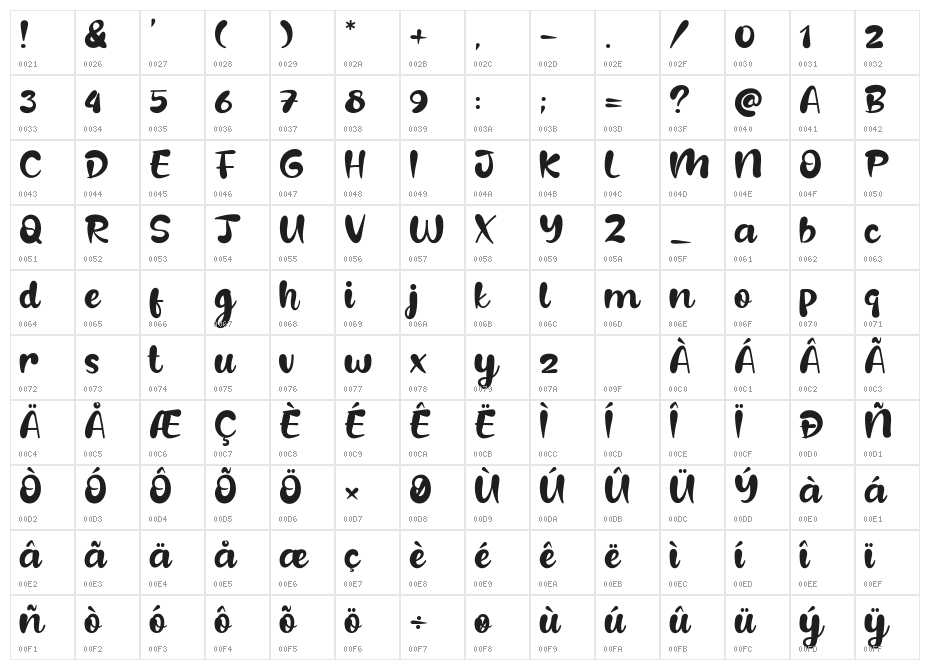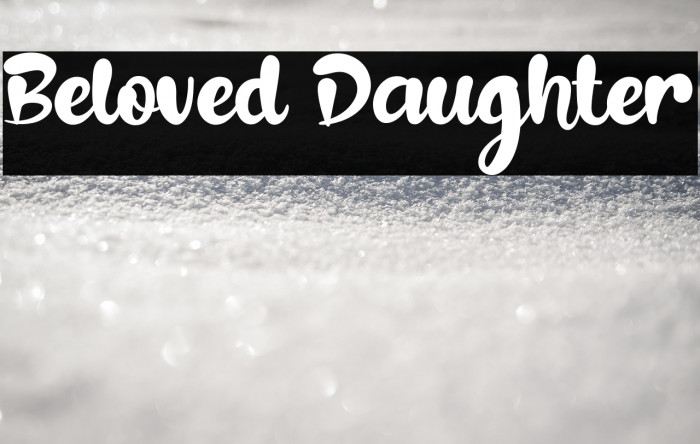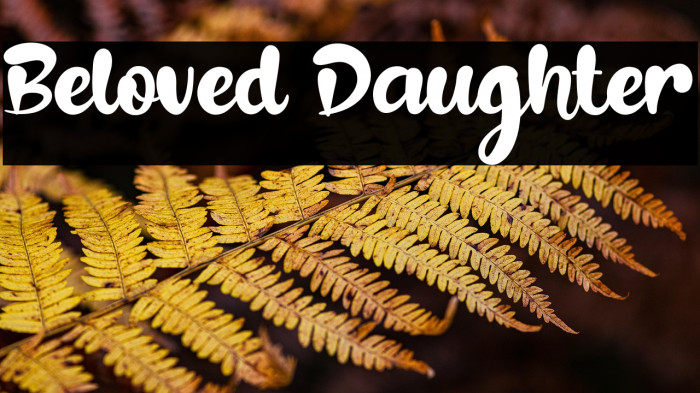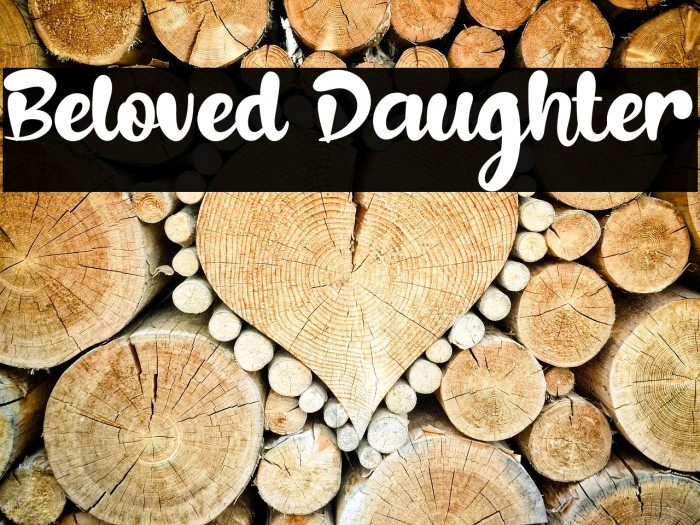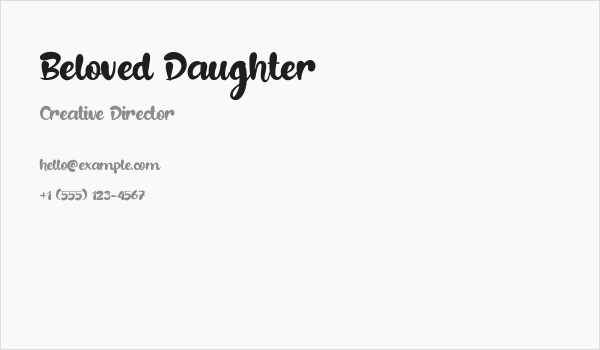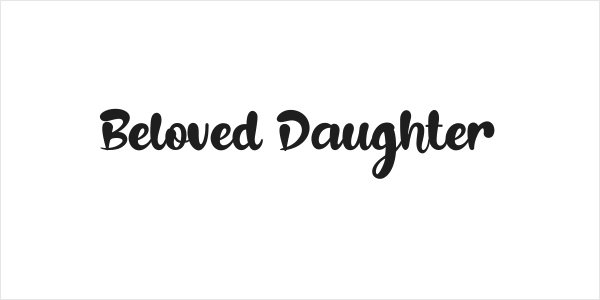
Beloved Daughter Font
| Caso d'uso | Logos, Headlines, Invitations |
| Progetti proposti | Ideal for greeting cards, invitations, playful branding, and children's book covers. |